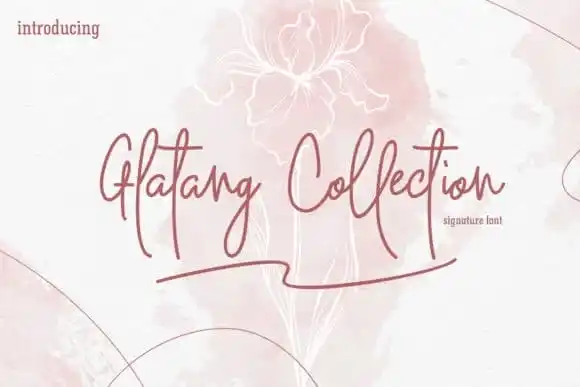
Glatang Collection Signature Font – Download Grátis
Seja bem-vindo ao Glatang Collection Signature Font, uma deliciosa escolha para designers que buscam um toque autêntico em suas criações. Esta elegante fonte feita à mão é uma combinação perfeita de elegância clássica e chamadas de arte realística. O resultado é uma experiência visual única que mantém seu aspecto tradicional, mas também oferece um ar amigável. O Glatang Collection Signature Font foi cuidadosamente criado pela BELOVE STUDIO em homenagem ao estilo tipográfico clássico, trazendo sua própria riqueza de estilo para qualquer projeto gráfico. Seja ele uma marca poderosa, um título inovador, um design de casamento ou até mesmo uma etiqueta personalizada – este font irá elevá-lo a outro nível. O Glatang Collection Signature Font é perfeito para qualquer projeto que exigir um toque especial e autêntico. Seja você criando algo profissional, artístico ou até mesmo algo divertido e casual, esta font será uma escolha inteligente. Não hesite em baixar seu arquivo agora e veja como ela pode transformar suas criações no design!